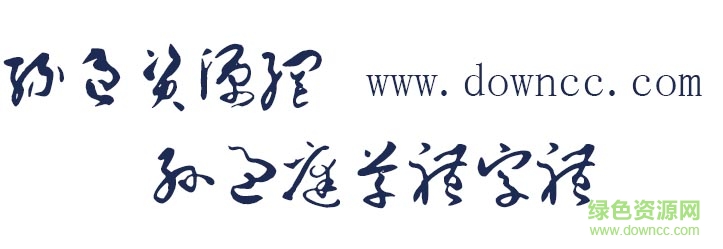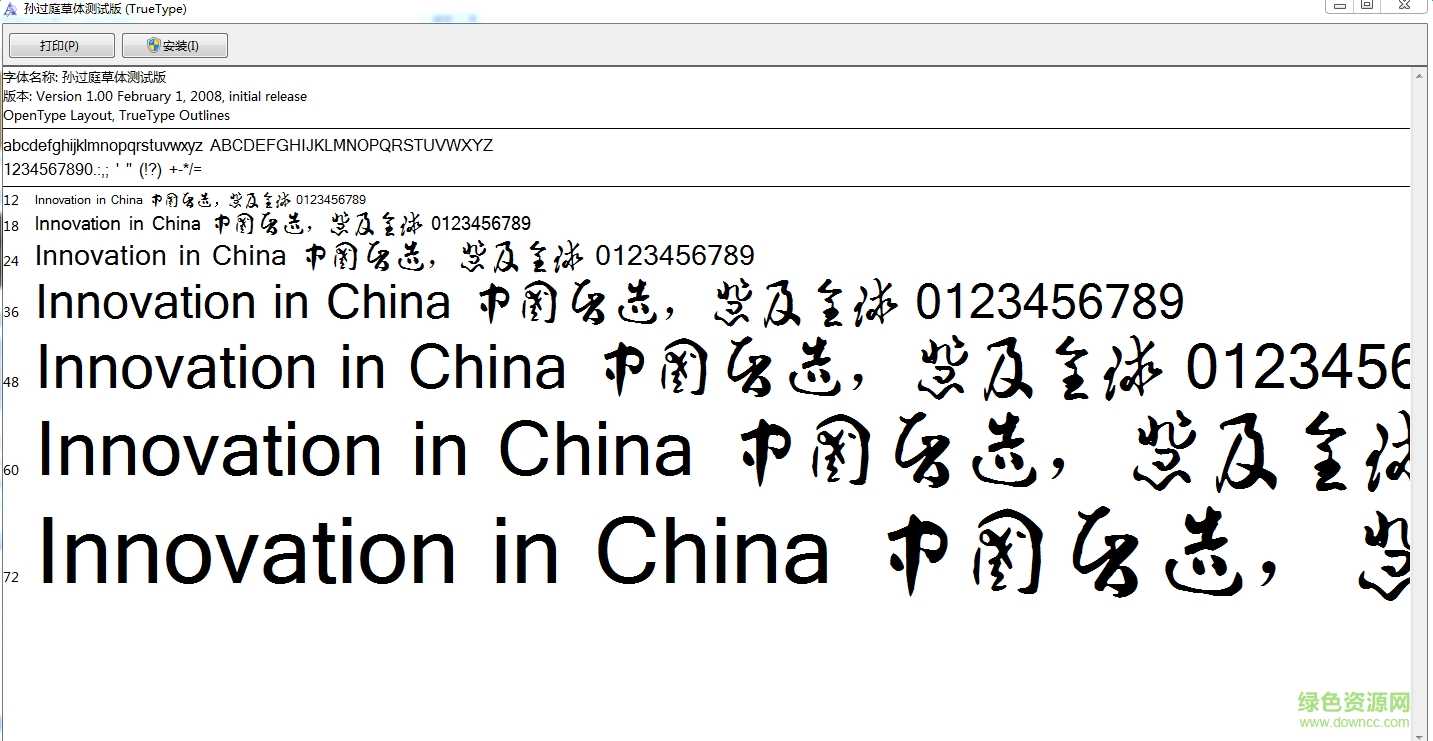
孫過(guò)庭草體字體是一款極具藝術(shù)價(jià)值的草書(shū)正式版字體,用筆恣肆,縱逸奔放,瀟灑又典雅,喜歡這款字體的朋友歡迎在綠色資源網(wǎng)下載收藏!
孫過(guò)庭草體是一款應(yīng)用于設(shè)計(jì)方面的的中文草書(shū)字體,該字體筆鋒犀利,威武有形,整體效果非常的出眾,可適用于牌扁設(shè)計(jì)、廣告設(shè)計(jì)、平面設(shè)計(jì)、印刷包裝等領(lǐng)域,有喜歡的朋友快下載收藏吧。